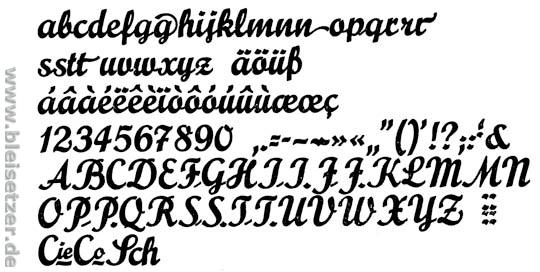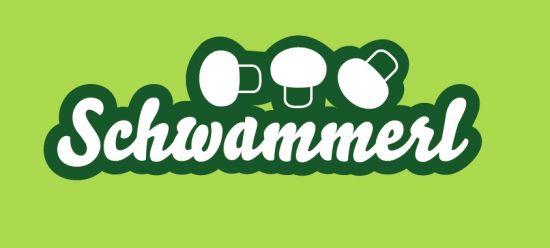
Candy Script - wer hat sie oder kennt ähnliche?
Ich brauche für ein privates T-Shirt einen Schriftzug - am liebsten in der Candy Script (bei Veer.de).
Wenn jemand die Candy hat und diesen "Auftrag" das eine Wort zu setzten übernehmen möchte, freue ich mich :-)
Oder gibt es eine sehr ähnliche Schrift als Freefont - oder zumindest für weniger als 99,- USD?
An die Bello habe ich auch schon gedacht, aber ich finde die nicht so gut speziell für dieses Wort:
Die anderen Tipps schaue ich mir an.
Noch eine andere Frage, wenn ich grade dabei bin. Gibt es fertige Swashes free oder welche Schrift kaufe ich da am besten?
Marcelle swashes heißt der Font, die Swashes sind so angenagt und knitterig wie bei verwitterten Plakaten.
Die Marcelle basiert auf Monotype Script bold, die wiederum auf der Prägefest (falls es mal nicht dreckig sein soll).
Marcelle swashes heißt der Font, die Swashes sind so angenagt und knitterig wie bei verwitterten Plakaten.
Die Marcelle basiert auf Monotype Script bold, die wiederum auf der Prägefest (falls es mal nicht dreckig sein soll).
Das ist die Prägefest
Ludwig & Mayer, Frankfurt am Main
Erstguß 1926
Eduard Lautenbach
Eure digitalen Fonts haben aber nicht soviele Varianten einzelner Lettern, richtig? :D
Mist. Na gut. Ich kaufe jetzt auf alle Fälle mal die schöne Bello und vielleicht opfert sich jemand von euch und setzt mir einen passenden swash im Illustrator - für irgendeine Gegenleistung. Das ist klar.
Das ist die Prägefest
Ludwig & Mayer, Frankfurt am Main
Erstguß 1926
Eduard Lautenbach
ich habe hier eine schriftprobe von der "offizin haag-drugulin", leipzig 1936
da ist die "prägefest" als "werbekursiv" abgebildet.
So sieht es jetzt aus :-)
Wie findet ihrs? Habt Ihr Verbesserungsvorschläge?
Ist wie gesagt ein privates Shirt.